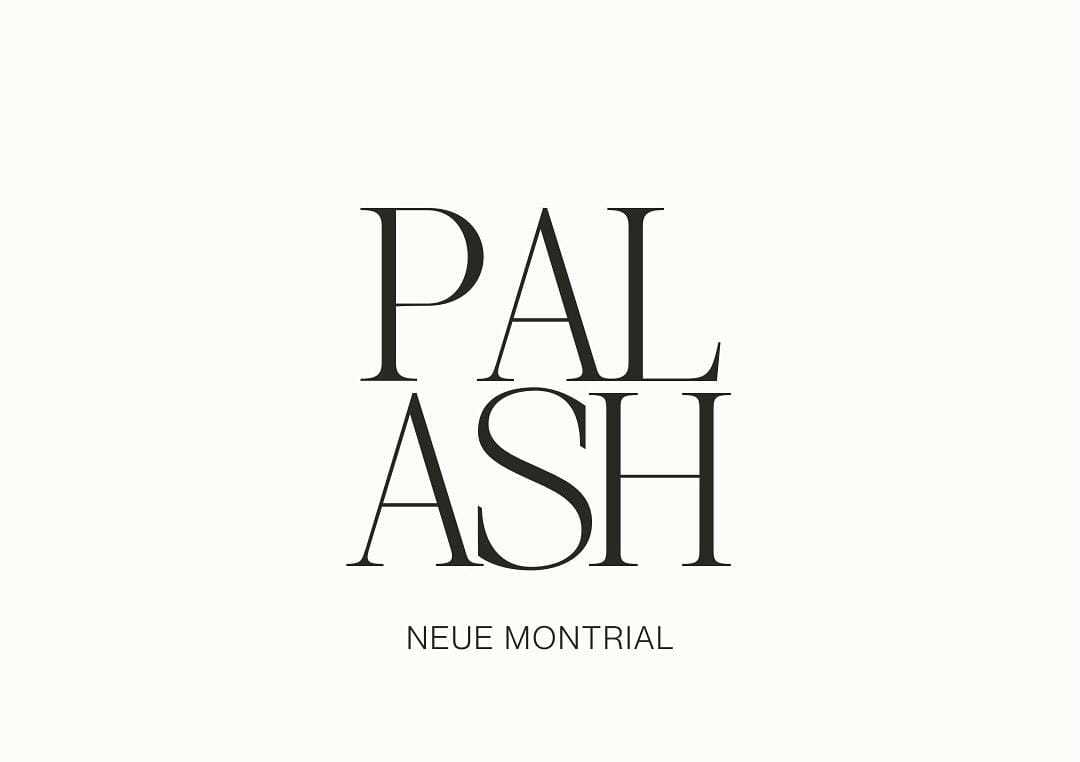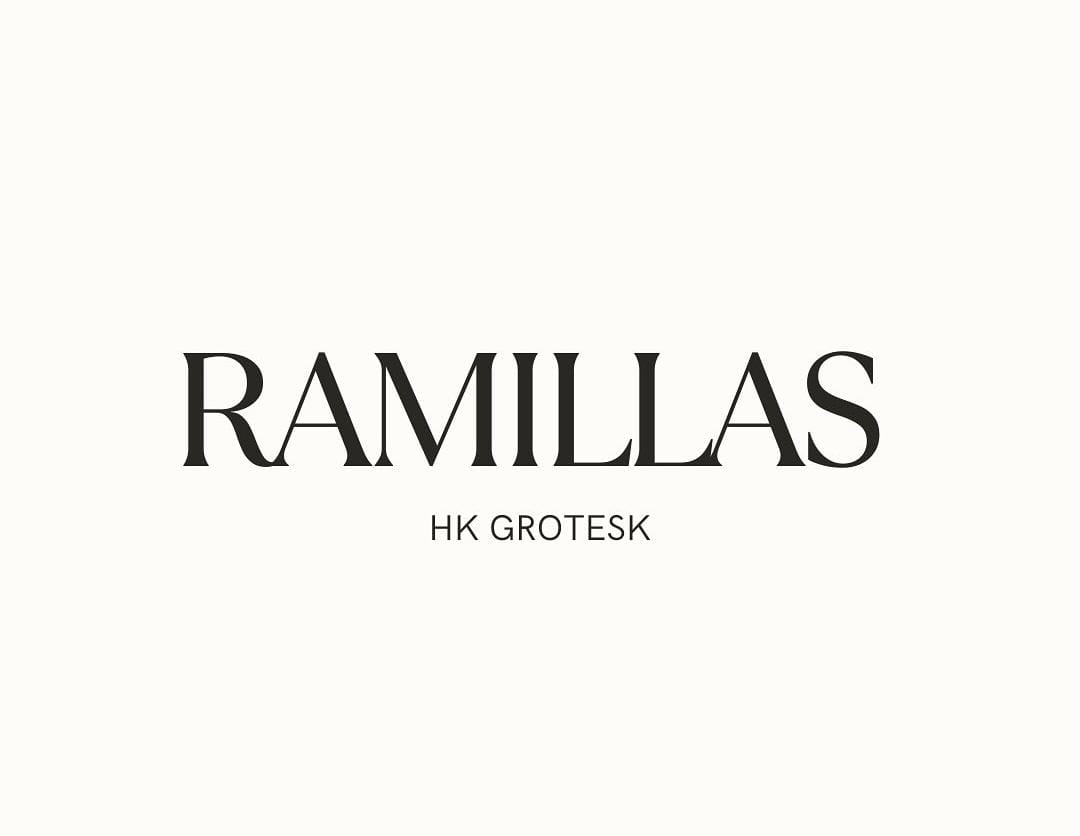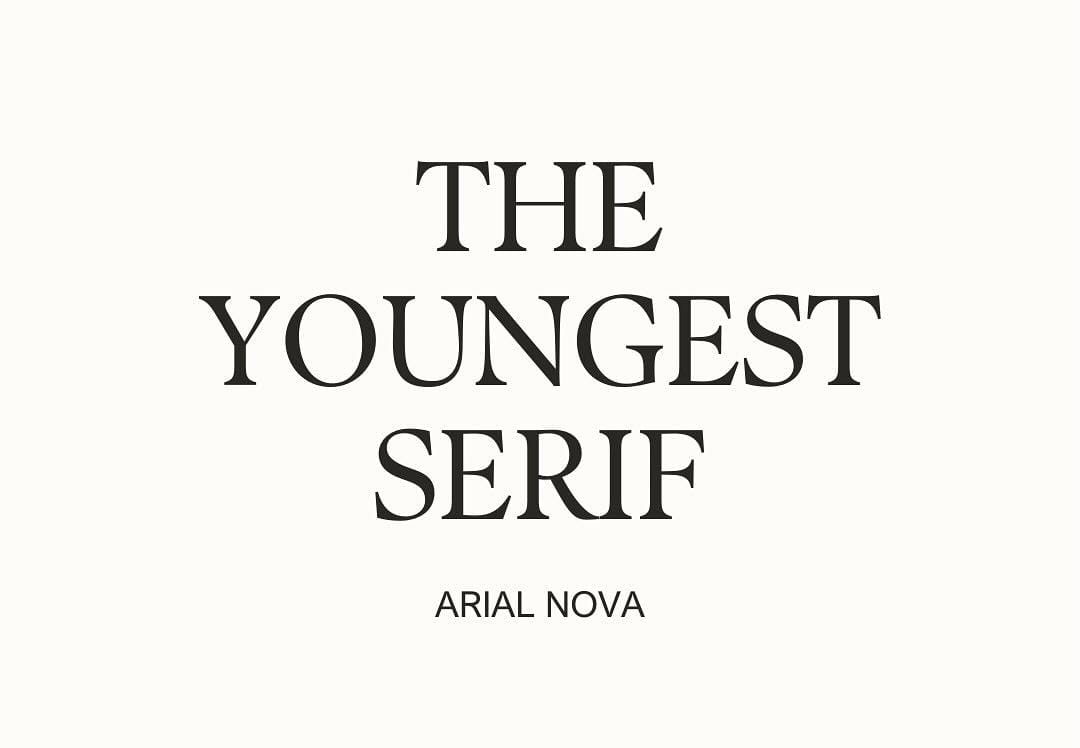
Kombinasi Font Elegan untuk Desain Logo Fotografi
<span;>Branding desain yang elegan akan lebih cocok merepresentasikan brand mewah, modern dan bergaya sederhana. Citra brand elegan pada logo fotografi akan membutuhkan tipografi, ikon dan warna yang sederhana. Kombinasi font elegan akan menciptakan desain logo fotografi yang minimalis dan bersih.
<span;>Desain logo akan tampil lebih estetik dan merepresentasikan identitas brand dengan baik jika menggunakan font elegan. Font elegan akan memiliki bentuk huruf sederhana, bersih dan mudah untuk dibaca. Logo akan tampil sederhana dan mudah beradaptasi jika menggunakan tipografi sederhana.
<span;>BRANDING BISNIS FOTOGRAFI
<span;>Bisnis fotografi seringkali menggunakan desain logo yang sederhana, bersih dan minimalis. Jenis bisnis fotografi untuk tujuan berbeda bisa menggunakan style logo berbeda. Misalnya logo fotografer wedding dan logo fotografer alam atau hewan akan memiliki estetika desain yang berbeda.
<span;>Gaya Elegan untuk Logo Fotografi Wedding
<span;>Dalam membangun identitas brand fotografi yang elegan, gunakan style desain logo elegan . Biasanya logo fotografi wedding akan memiliki desain yang sederhana dan bersih. Logo elegan akan merepresentasikan citra brand fotografi untuk wedding dengan relevan. Desain logo elegan akan merepresentasikan bisnis fotografi untuk pernikahan dengan jelas dan menarik.
<span;>Style Modern untuk Logo Fotografer Umum
<span;>Sementara itu untuk branding desain logo fotografi umum seperti untuk kebutuhan foto keluarga, pribadi atau album sekolah akan tampil lebih sederhana. Untuk desain logo fotografer umum bisa menggunakan style sederhana, modern dan bergaya geometris. Gaya modern akan menciptakan kesan logo yang tetap relevan dan tampil trendy. Biasanya warna logo juga akan sederhana sehingga akan tetap sederhana.
<span;>Style Alami dan Santai Untuk Logo Fotografi Alam dan Hewan
<span;>Sementara itu untuk desain branding logo fotografi alam gunakan style sederhana dan penggunaan gambar alam. Gambar alam seperti daun atau gambar hewan akan merepresentasikan fotografi terkait alam.
Desain tetap harus sederhana dan menggunakan style gambar line art atau siluet agar berkesan elegan. Gambar alam akan menciptakan kesan alami sehingga bisa membangun branding yang relevan.
<span;>Logo Fotografi Produk yang Bergaya Modern
<span;>Bisnis fotografi saat ini memiliki layanan yang khusus agar lebih profesional, termasuk untuk kebutuhan foto produk. Branding bisnis fotografi produk bisa memiliki style yang sederhana. Gaya fotografi modern akan menggunakan bentuk gambar yang sederhana, bentuk geometris dan tipografi sederhana. Logo juga akan memiliki warna sederhana seperti warna hitam dan putih.
<span;>KOMBINASI FONT UNTUK LOGO FOTOGRAFI
<span;>Untuk digunakan sebagai branding bisnis fotografi, gunakan gaya tipografi yang sederhana dan elegan. Kombinasi font sans serif dan serif elegan akan cocok untuk logo fotografi. Kombinasi font akan menciptakan kesan brand elegan, profesional dan dapat dipercaya.
<span;>The Youngest Serif dan Arial Nova
<span;>Kombinasi font serif elegan tersebut akan menciptakan desain elegan dan memiliki tampilan yang bersih. Gaya font serif modern tersebut dikombinasikan dengan font sans serif sederhana. Kombinasi font tersebut akan menciptakan desain logo fotografi elegan, modern dan tampil minimalis.
<span;>Gaya tipografi yang elegan dan bersih ini akan relevan untuk merepresentasikan bisnis fotografi umum atau fotografi produk. Gunakan juga style ikon sederhana dengan garis halus agar menciptakan kombinasi yang harmonis
<span;>Palash dan Neue Montrial
<span;>Desain logo fotografi seringkali memiliki visual yang elegan dan estetik sehingga cocok dengan desain yang sederhana. Kombinasi tipografi yang sederhana dan bersih juga memudahkan nama brand dibaca dan diingat. Font serif bergaya elegan dengan ujung serif lancip tersebut akan merepresentasikan brand fotografi yang elegan.
<span;>Kombinasi font serif dan sans serif sederhana tersebut bisa membangun branding bisnis fotografi wedding yang elegan. Logo untuk fotografi produk kecantikan juga bisa menggunakan kombinasi font elegan tersebut. Kontras gaya huruf tebal dan tipis menciptakan desain logo yang akan tampil modern.
<span;>Tan Angleton dan Inter
<span;>Branding bisnis fotografi yang tampak bersih dan sederhana akan menciptakan kesan bisnis profesional dan terpercaya. Kombinasi gaya font serif dan sans serif akan menampilkan kombinasi harmonis. Gunakan style font serif elegan  kombinasikan dengan font sederhana pula.
<span;>Kombinasi font elegan pada logo fotografi juga harus kontras agar kombinasi menciptakan hirarki visual yang jelas. Font serif elegan tersebut tampak kontras dengan font serif yang digunakan. Tipografi tersebut bisa digunakan untuk logo fotografi branding bisnis fotografi yang profesional dan handal.
<span;>KESIMPULAN
<span;>Gaya tipografi logo untuk bisnis fotografi akan memiliki ciri sederhana, elegan dan mudah untuk dibaca. Kombinasi font elegan akan menciptakan desain logo fotografi yang elegan, profesional dan handal. Font serif dan sans serif termasuk yang sering digunakan, jenis font script juga bisa digunakan jika untuk logo fotografi wedding.